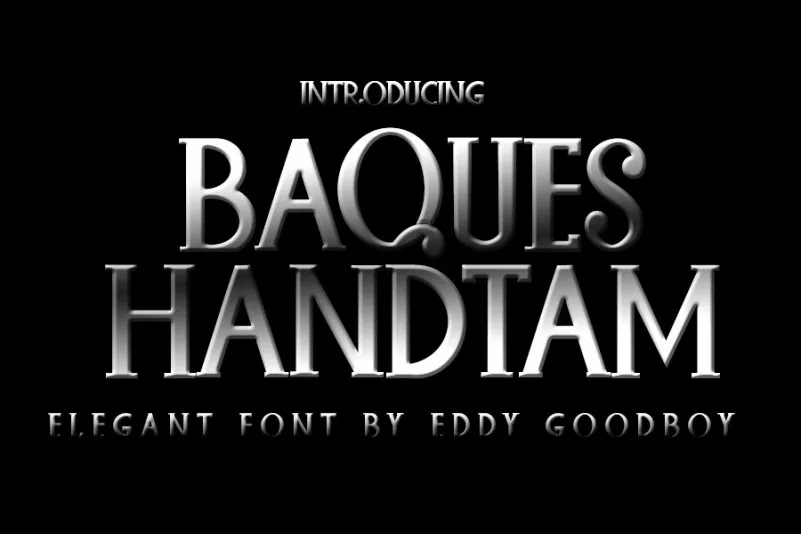
Baques Handtam Font – Download Grátis
Baques Handtam Font é uma elegante fonte slab serif criada por Eddygoodboy com detalhes delicados e refinados. Sua simetria e proporção são perfeitas, tornando-a ideal para um amplo espectro de projetos gráficos, desde cartões de convidado para casamentos até logotipos e cards de negócios. Ideal para aqueles buscando uma fonte que transmite elegância sem ser formal, o Baques Handtam é perfeito para estilos artísticos ou modernistas que valorizam um toque autêntico à mão em seus projetos design. Seja você um designer criativo ou um usuário final de designs casuais, este tipo de fonte oferece uma solução versátil e sofisticada para qualquer projeto que precise de um toque especial.